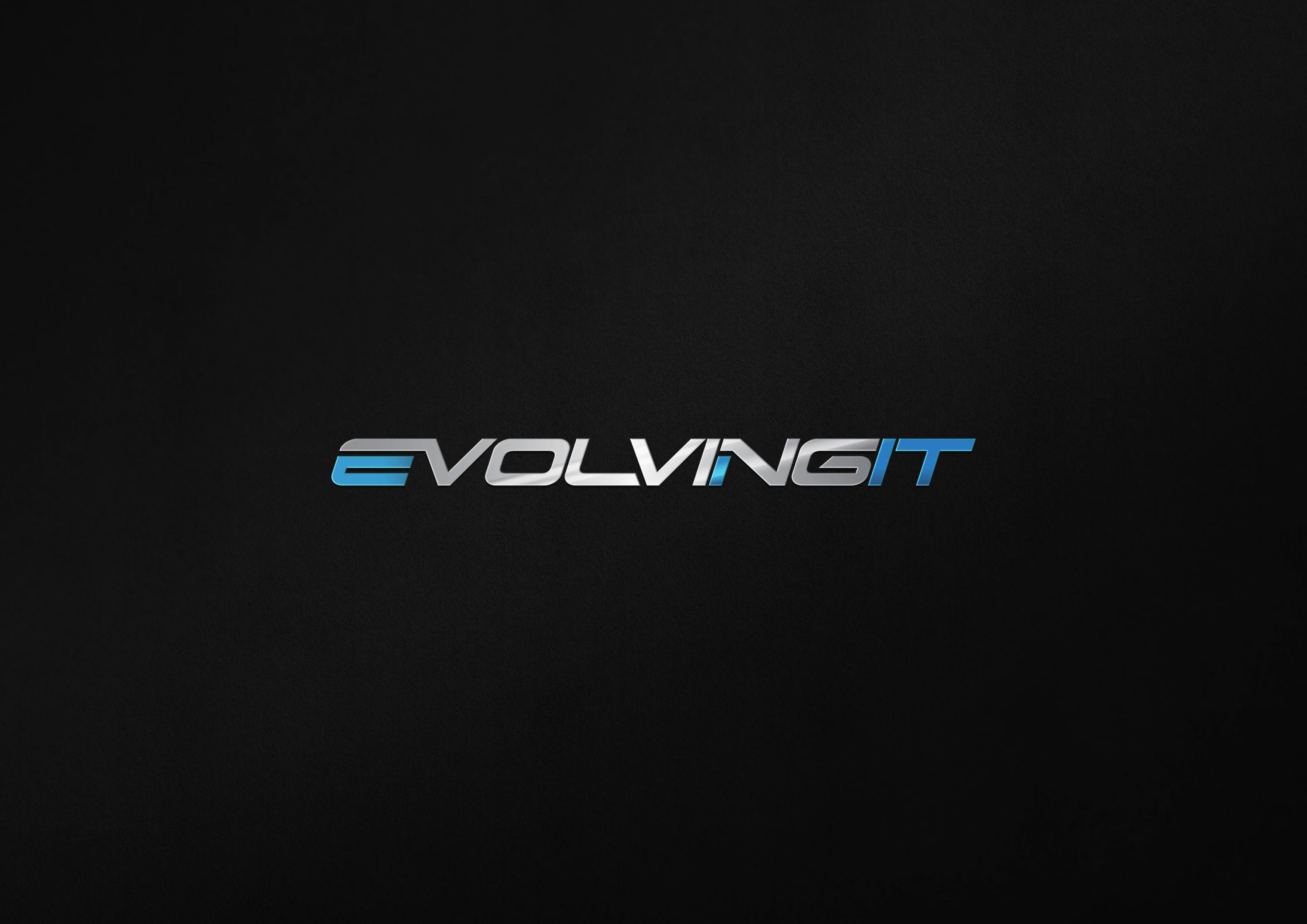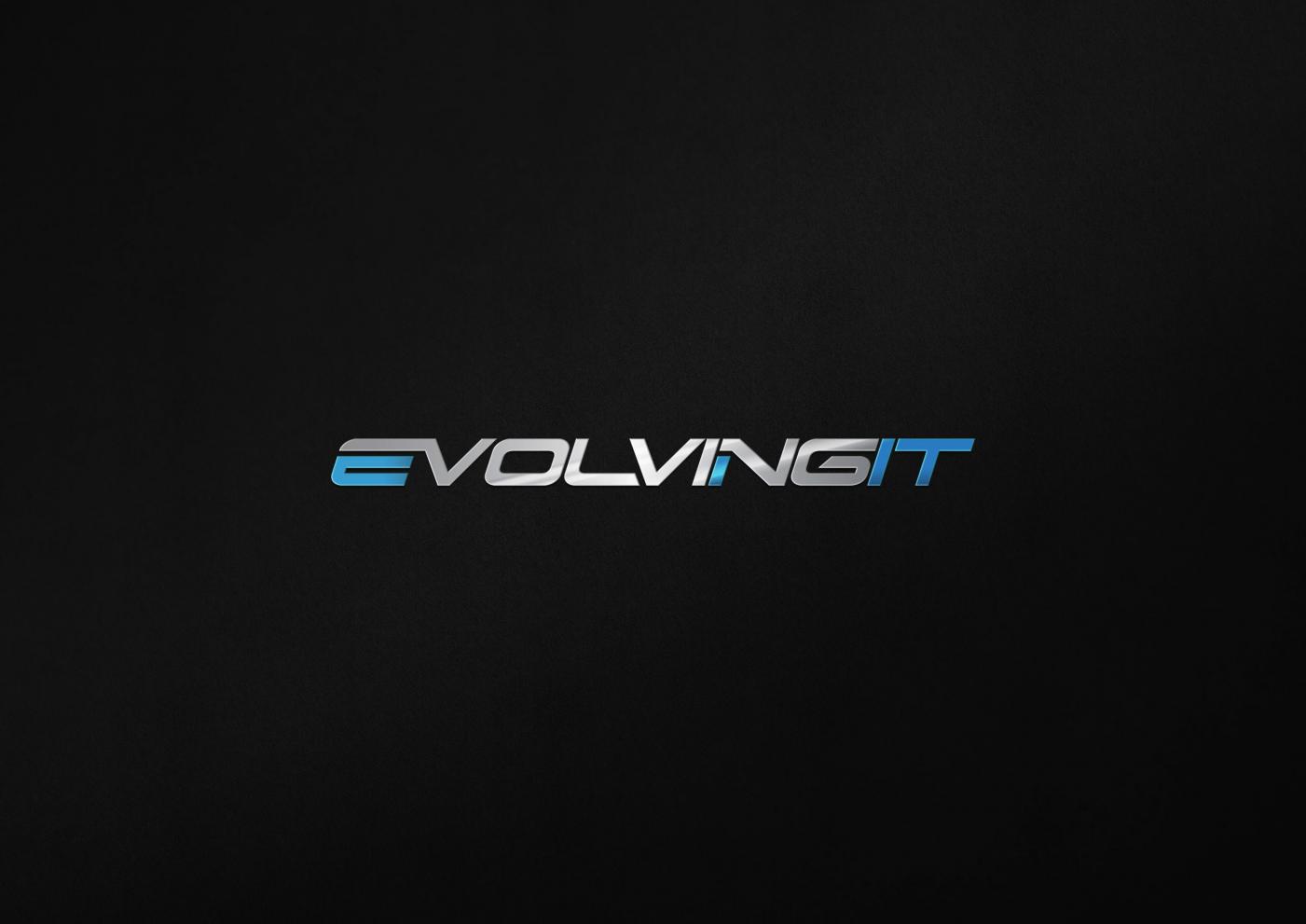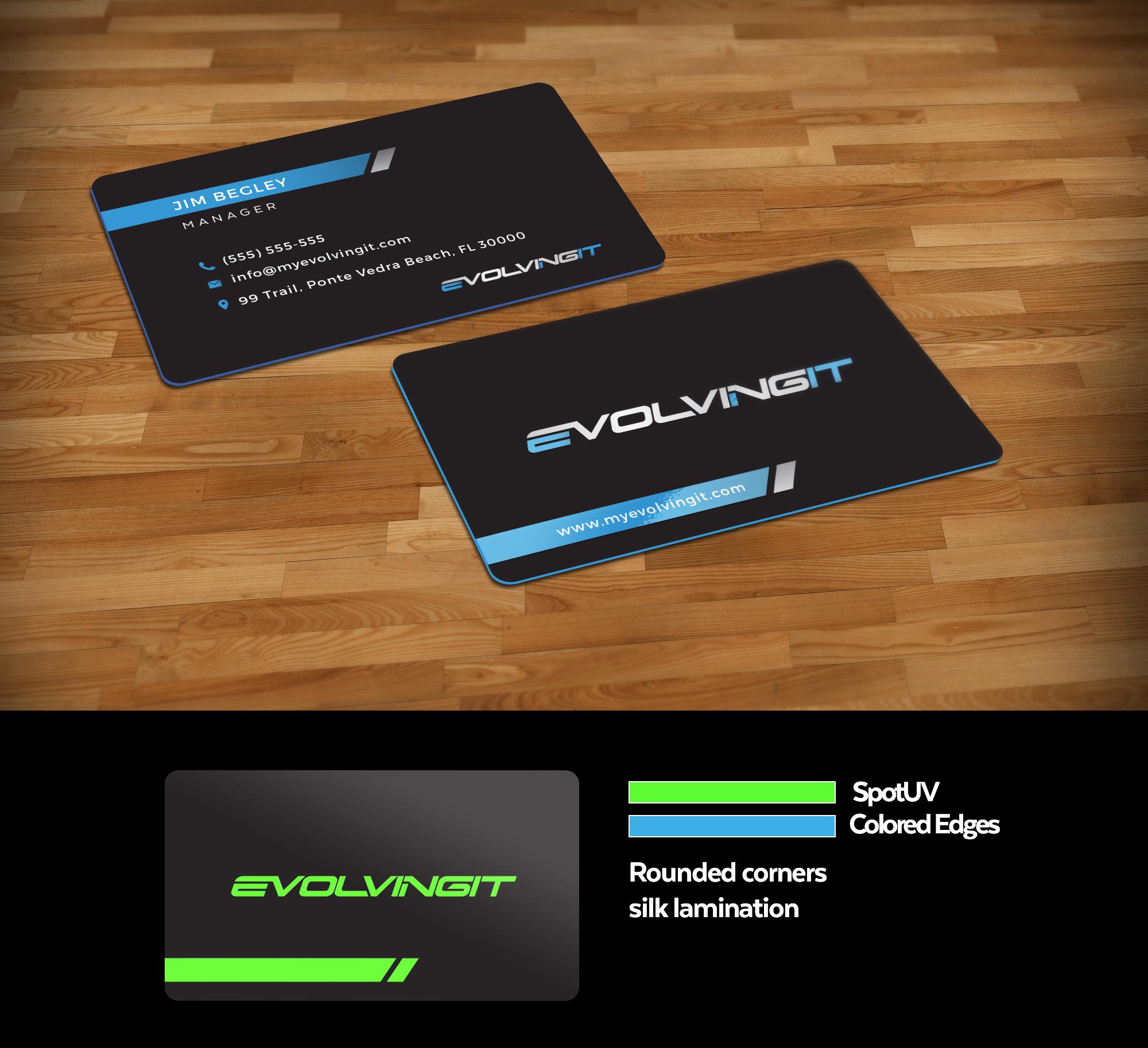
Evolvingit - Schriftart?
ich habe auf einer Homepage ( https://99designs.de/profiles/ultrastjarna?page=5 )ein Bild gesehen und finde die Schriftart so toll, kann mir jemand sagen, wie diese Schriftart sich nennt?
Ich habe die schon ein paar mal gesehen, aber nie den passenden Namen dazu gefunden, wonach ich die Schriftart verwenden kann.
ich befürchte, dass ist eine Handarbeit, also eine Umbau, auf der Basis einer schon bestehenden Schrift. Ich hätte da Terminator Two gefunden. Auf Dafont habe ich die nicht gefunden, aber sehr ähnliches ...
Das scheint eine Anleihe an Terminator Two zu sein?
Es kann aber auch durchaus keine vorhandene Schriftart dahinter stecken. Schließlich hat die vorhandenen Schriftarten ja auch mal jemand gezeichnet. Wenn man jetzt eine Schrift entwirft, muss man ja mit allen Buchstaben, Ziffern und Satzzeichen so ab 200 zusammen passende Schriftzeichen zeichnen. Viele davon gehen dabei zwar aus anderen hervor. Will man dann noch Griechisch ins Kyrillisch, und jeweils alle Sondervarianten für x Sprachen unterstützen, kommt man gut auf über 1000 Schriftzeichen.
Wenn es jetzt nur um ein Logo geht, sind hier ja gerade einmal 8 unterschiedliche Schriftzeichen zu zeichnen. Da würde ich nicht Stunden für die Suche nach einer Schrift suchen, die so aussieht, wie ich mir das Logo vorstelle.